タイポグラフィ13 タイポグラフィ事典
文字を楽しむデザインジャーナル「Typography(タイポグラフィ)」の13号として「タイポグラフィ13 タイポグラフィ事典」がグラフィック社から2018年5月8日に発売される。
字を楽しむデザインジャーナル『Typography(タイポグラフィ)』の13号。
特集となり「タイポグラフィ事典」ではこれまで「Typography(タイポグラフィ)」で掲載してきた手書き文字やフォント、組版などを40項目に分類して事典形式で紹介する永久保存版。
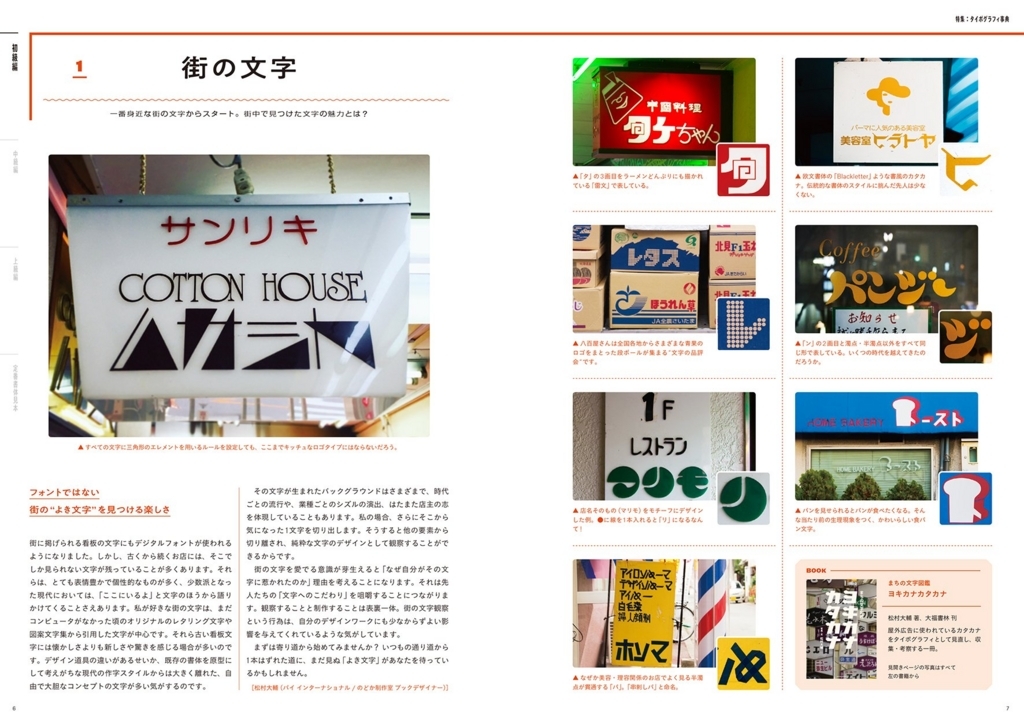
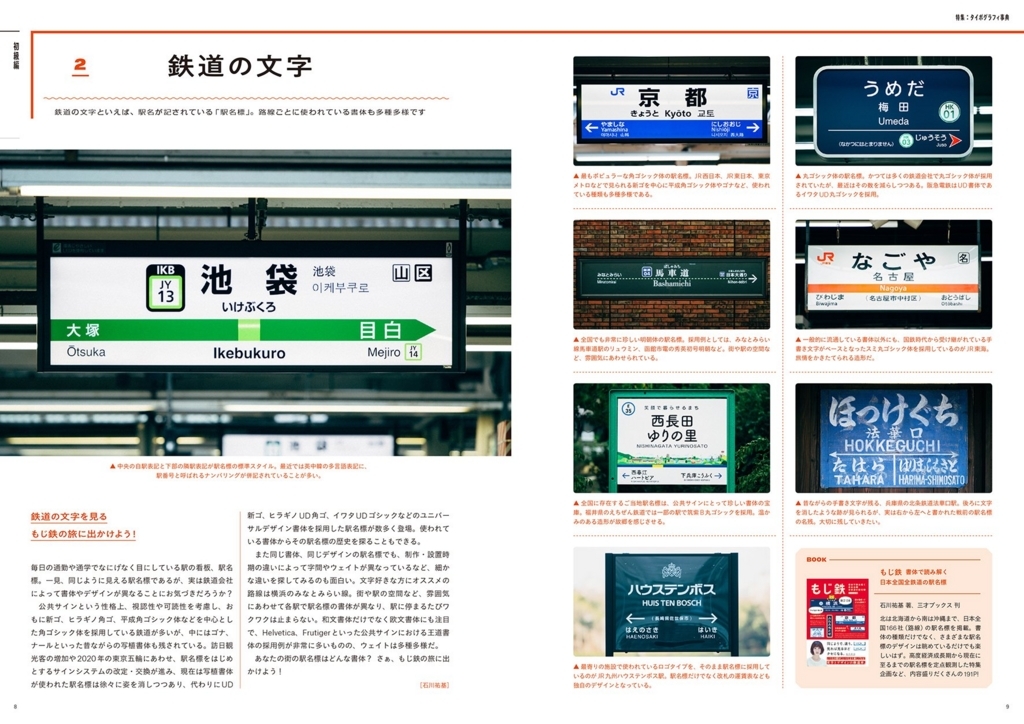
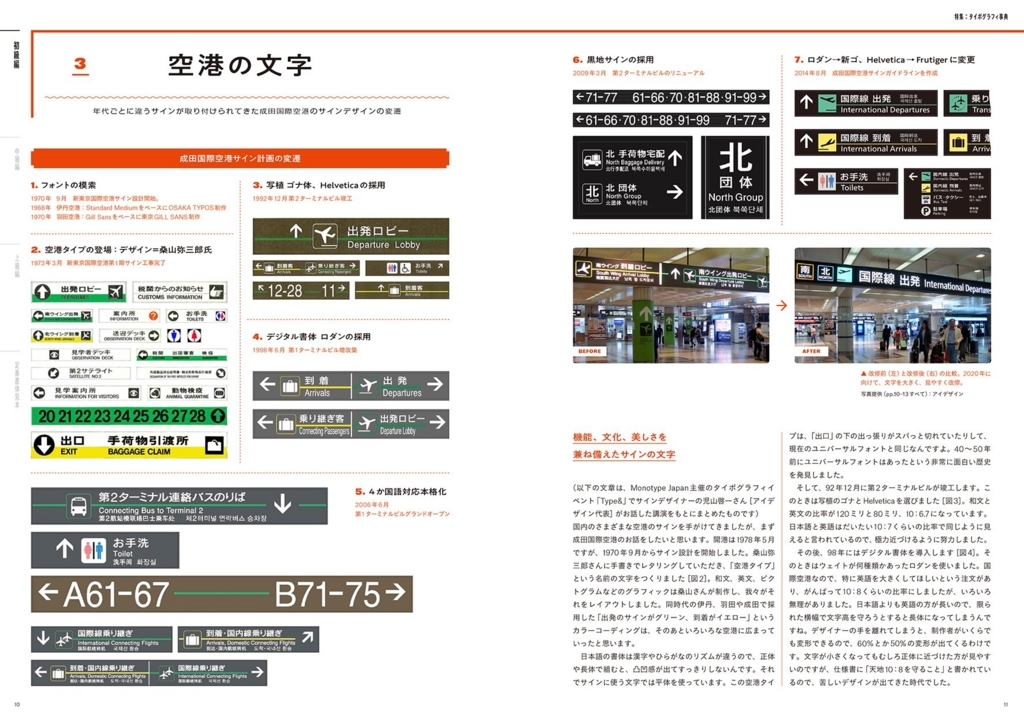
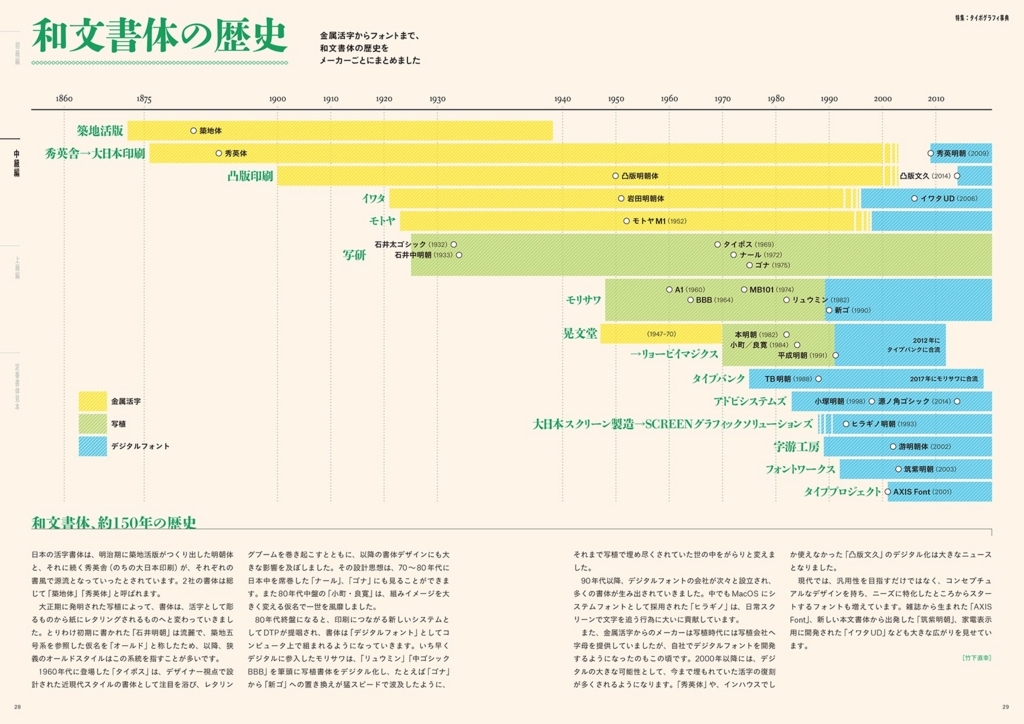
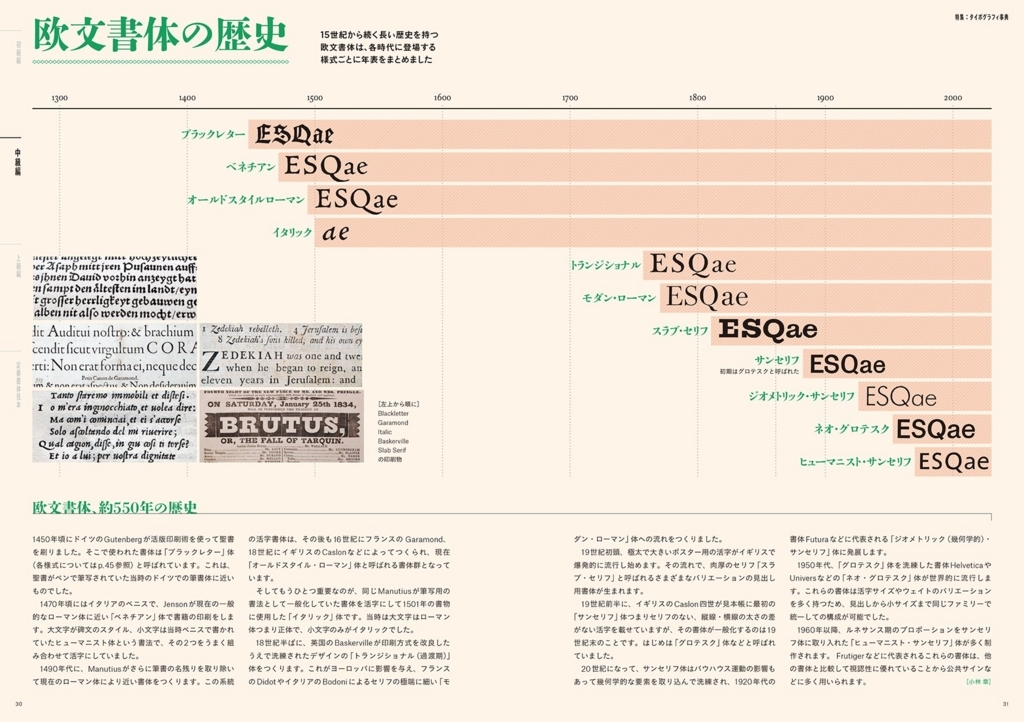
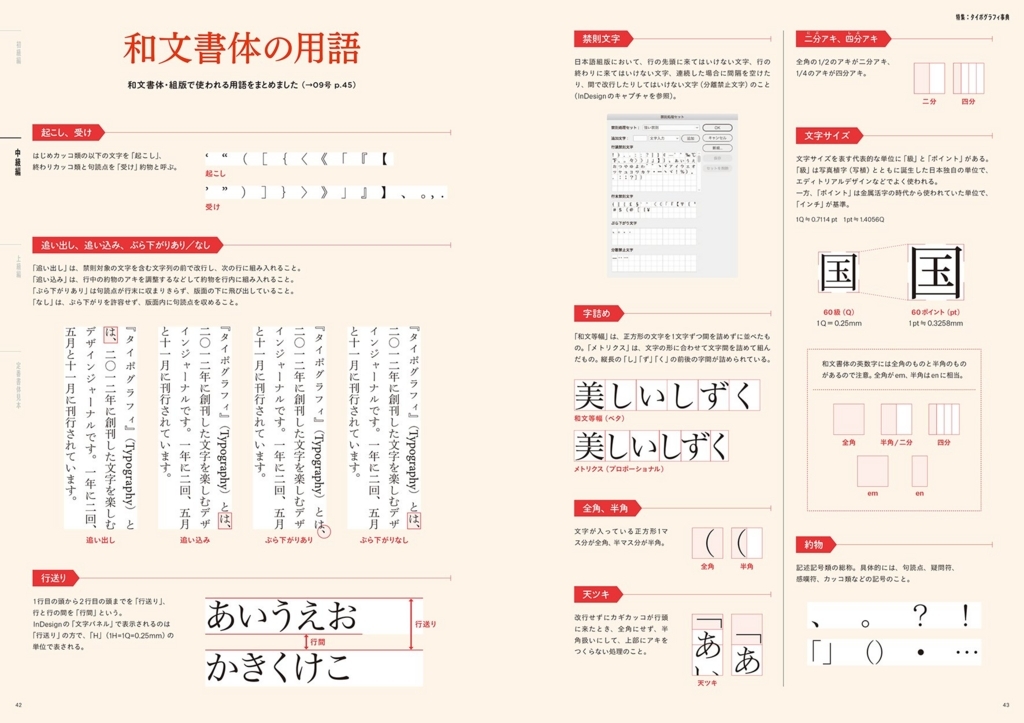
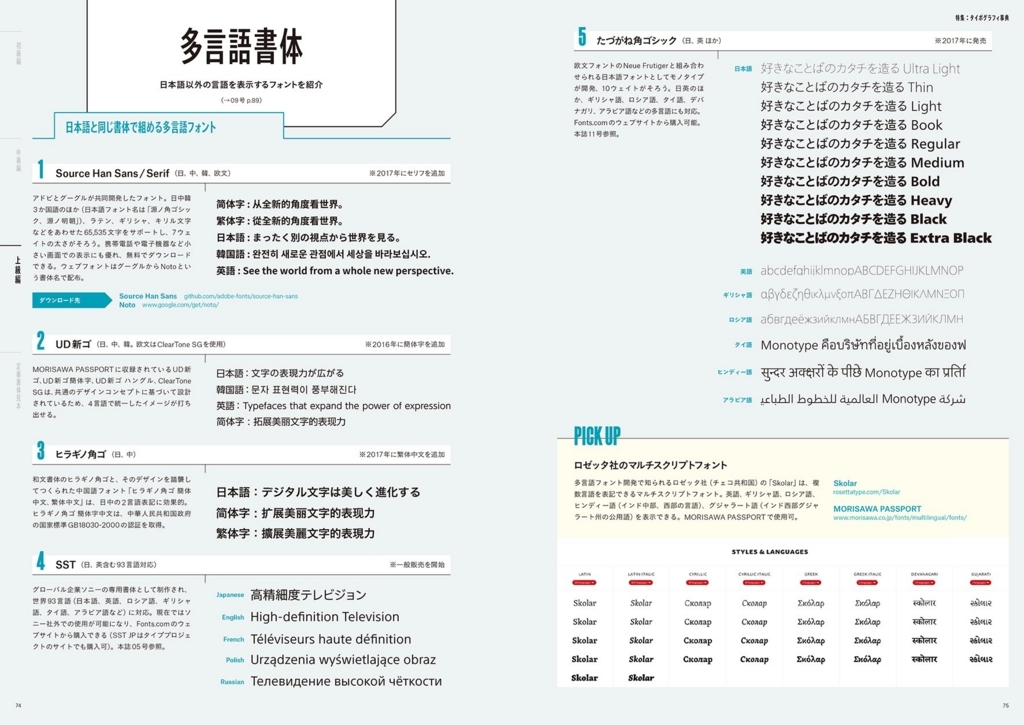
文字を楽しむデザインジャーナル『Typography(タイポグラフィ)』の13号。
特集は「タイポグラフィ事典」。
今までに掲載した手書き文字、フォント、組版など
40 項目を事典形式で紹介した永久保存版です。
街の看板、電車の駅名標、空港のサイン、ゲームの文字など、
身の回りの文字を紹介する初級編、
デザイナーに役立つフォントや組版の知識をまとめた中級編、
多言語フォントやカスタムフォントなど最新動向を解説する上級編、
和文と欧文の定番フォント400 書体を掲載した定番書体見本編。
文字に関する情報が網羅され、辞書のように使える便利な一冊です。
【目次】
特集「タイポグラフィ事典」
初級編 身のまわりの文字
・ 街の文字
・ 鉄道の文字
・ 空港の文字
・ ブランドの文字 ・ パッケージの文字
・ ゲームの文字
・ 漫画の文字
・ 書籍の文字
・ 活版の文字
・ 腕時計の文字
・ 手書きの文字
・ かるたの文字
中級編 書体と組版
・ 書体のなりたち
・ 和文書体の歴史
・ 欧文書体の歴史
・ 和文書体メーカー
・ 欧文書体メーカー
・ 和文書体のロゴ使用
・ 和文書体の用語
・ 欧文書体の用語
・ 特殊文字の出し方
・ グリフの調べ方
・ 本文組版
・ 書籍の組版設定
・ 活字の組版
・ 写植・その他の組版
・ スクール&イベント
・ ウェブフォント
・ ウェブの組版
上級編 多言語とカスタムフォント
・ 多言語書体
・ 多言語組版
・ カスタムフォント
・ フォント作成ツール
・ Glyphsを使ったフォント作成
定番書体見本編
・ 和文書体 見出し
・ 和文書体 本文
・ 欧文書体 セリフ
・ 欧文書体 サンセリフ
・ 欧文書体 スクリプト
・ 欧文書体 ディスプレイ
・「モリサワ新書体見本帳」
2017年5月20日に発売された「タイポグラフィ」の11号では欧文書体を特集。パッケージや書籍などで欧文書体が使われているヨーロッパの実例、欧文書体の高度の使用方法を紹介。
文字を楽しむデザインジャーナル『Typography(タイポグラフィ)』の11号。
特集は「欧文書体を使いこなす」。いつも同じ書体ばかり使ってしまう
マンネリから卒業できる、ワンランク上の欧文書体の使い方を紹介します。
書籍、パッケージ、ウェブなど、ヨーロッパの最新事例から
効果的な欧文書体の使い方が学べます。知っておきたい欧文書体の基礎知識や
用語解説も掲載し、初心者から上級者まで活用できる内容になっています。
また、本誌特別付録として、定番200書体の書体見本を掲載した小冊子と、
和文フォントと欧文フォントの組み合わせ例を紹介した小冊子
(いずれもA5判48ページ)がついています。
【目次】
ヨーロッパの事例から学ぶ欧文書体の選び方と使い方
[事例1]ドイツの新聞「Welt」
[事例2]日産の3つの専用書体
[事例3]Monotypeの新書体開発
[事例]欧文書体の上手な使い方 書籍、パッケージ、ウェブサイト
知っておきたい欧文フォントの知識 Q&A
欧文書体の用語解説
欧文書体の超基本 定番書体と使い方 ほか
【付録小冊子】
・欧文書体の定番書体200を紹介した書体見本帳
・和文フォントと欧文フォントの組み合わせ例を紹介した書体見本帳
2016年11月8日に発売されたタイポグラフィ10号では、日本語のロゴとタイトルが特集された。デザイナーへのインタビューや日本語ロゴの紹介、筆文字ロゴの書家リスト、タイトルで使えるフォントの書体見本、フォントをロゴやタイトルに使うときの使用規約などを紹介。
デザイナーへのインタビュー、日本語ロゴの作品紹介、筆文字ロゴの書家リスト、
タイトルで使えるフォントの書体見本、フォントをロゴやタイトルに使うときの
使用規約などを紹介。付録小冊子2冊つき。
【特集】
日本語のロゴとタイトル
・CLOSE UP 1 とらやの羊羹のロゴ
サン・アド(葛西薫+制作チーム)
・CLOSE UP 2 越後亀紺屋 藤岡染工場のロゴ
フレーム(石川竜太)
・CLOSE UP 3 夏詣+土木展のロゴ
10 inc.(柿木原政広)
・デザイナー10組の日本語ロゴとタイトル文字
・筆文字ロゴの書道作家と作品
・一人の書家が書いた約60書体の筆文字フォント
・文字のバランス構成テクニック
・タイトルで使える和文書体
・タイトルで使える欧文書体
・タイトル文字から本文までカバーするオプティカル・サイズのフォント
・和文フォントのロゴ使用 ロゴやタイトル文字に使う時の規約一覧
[特別記事・連載]
・Report 1:「小村雪岱と資生堂書体」展
・Report 2:TypeCon 2016
・Hot New Fonts akira1975
・Book Typography 麥倉聖子
・文字の裏ワザ 小林 章
・ルーツで見分ける和文書体 竹下直幸
・バックナンバー
・10号特別付録紹介
[特別付録]
・特大から極小まで使える欧文フォント「オプティカルサイズ書体見本帳」
・モリサワパスポートマガジン